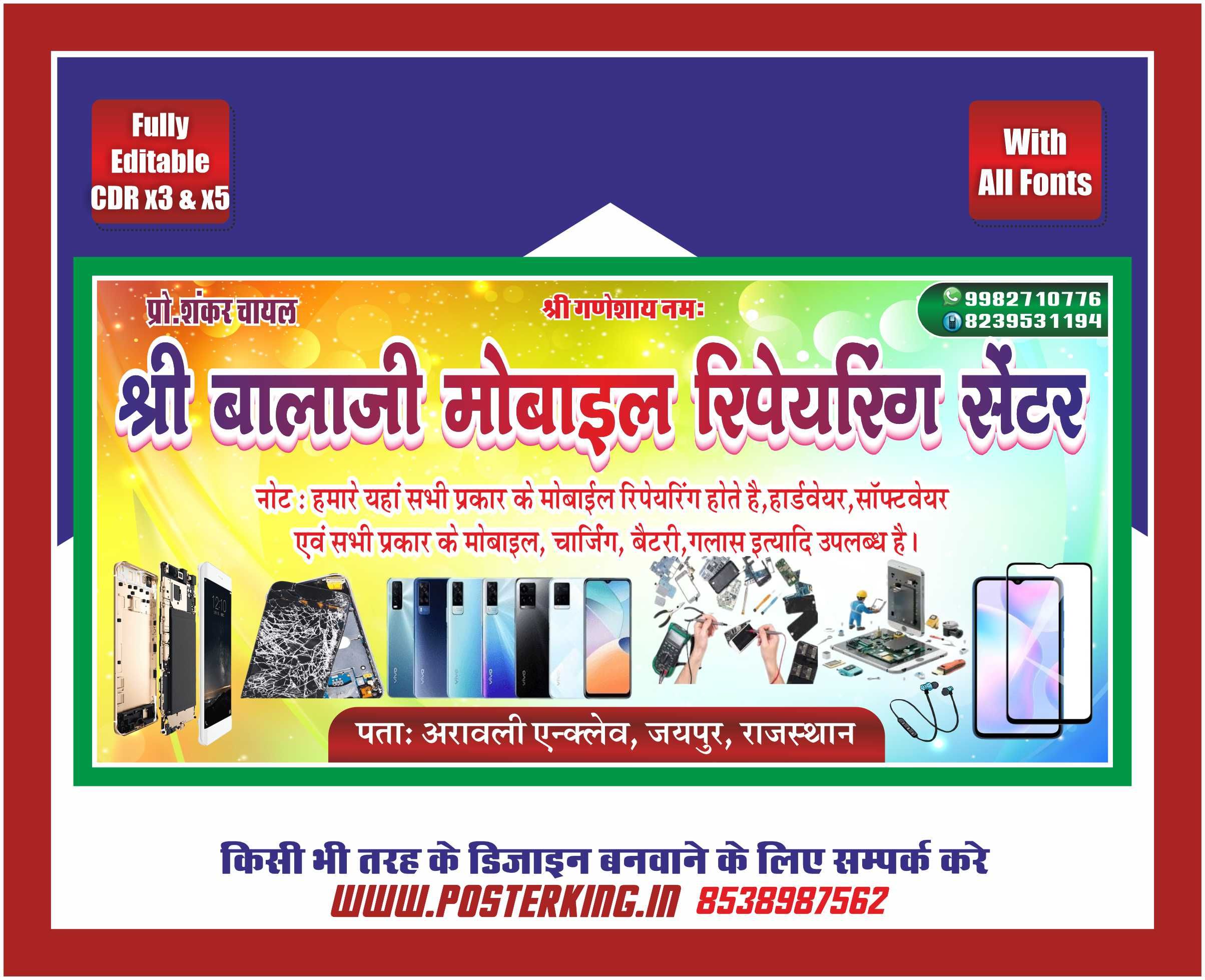
Modern Gadget Repairing Service Banner with Fonts
यह डिजिटल फ़ाइल विशेष रूप से मोबाइल रिपेयरिंग शॉप, गैजेट सर्विस सेंटर और इलेक्ट्रॉनिक्स स्टोर के लिए तैयार की गई एक पेशेवर विज्ञापन सामग्री है। इस बैनर का लेआउट आधुनिक तकनीक और ग्राहक के विश्वास को ध्यान में रखते हुए बनाया गया है, जो किसी भी बाज़ार या सड़क किनारे लगी दुकान की ओर लोगों का ध्यान तुरंत खींचने में सक्षम है।
डिज़ाइन की मुख्य विशेषताएँ:
• आकर्षक ग्राफ़िक्स: बैनर में टूटी हुई मोबाइल स्क्रीन, रिपेयरिंग टूल्स, नए स्मार्टफ़ोन और टेम्पर्ड ग्लास के हाई-रिज़ॉल्यूशन चित्रों का उपयोग किया गया है, जो सीधे आपकी सेवाओं को प्रदर्शित करते हैं।
• व्यापक सेवा सूची: इसमें स्पष्ट रूप से लिखा गया है कि यहाँ सभी प्रकार के मोबाइल का सॉफ्टवेयर, हार्डवेयर, चार्जिंग समस्या, बैटरी रिप्लेसमेंट और ग्लास बदलने का कार्य कुशलतापूर्वक किया जाता है।
• प्रोफेशनल हेडर: मुख्य शीर्षक “श्री बालाजी मोबाइल रिपेयरिंग सेंटर” को 3D इफ़ेक्ट और साफ़ फॉन्ट्स में सजाया गया है।
• प्रीमियम बैकग्राउंड: पीले और नारंगी रंग का चमकता हुआ बैकग्राउंड (Sparkle Background) दुकान की दृश्यता (Visibility) को बढ़ाता है।
• Modern Tech Layout: मोबाइल रिपेयरिंग और सर्विसिंग व्यवसाय के लिए एकदम सटीक और पेशेवर डिज़ाइन।
• Service Transparency: हार्डवेयर और सॉफ्टवेयर से जुड़ी सभी सेवाओं का स्पष्ट उल्लेख।